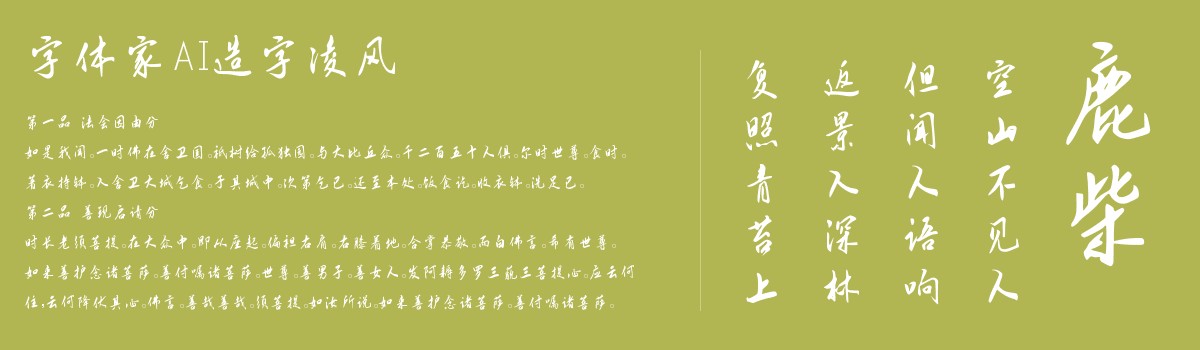
字体家AI造字凌风
字体家AI造字凌风是一款由字体家AI神笔造字生成的一款艺术字体,这是一款手写风格字体,线条流畅自然,似随笔勾勒。笔画有细腻的粗细变化,起收笔圆润柔和,无生硬棱角。横画略呈弧度,竖画挺拔却不僵直,撇捺舒展轻盈,如羽翼轻展。整体结构疏密有致,不局促不松散,带着手写的灵动与温和,无刻意装饰,像春日微风拂过纸面,留下飘逸又亲切的痕迹。比较适合用于艺术类装饰文字,海报、网页、广告设计,室内装饰,平面标题设计、食品包装、品牌标志等。